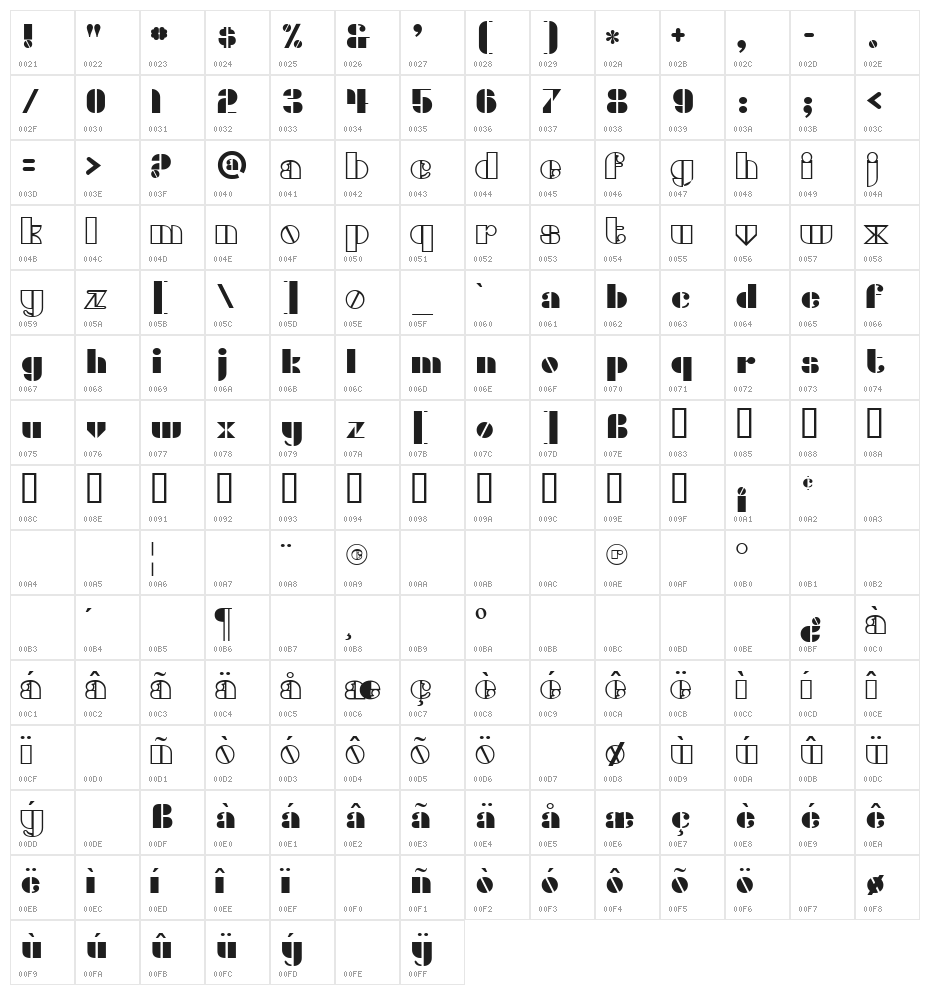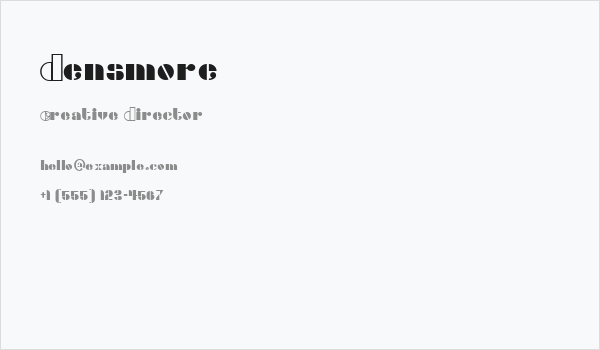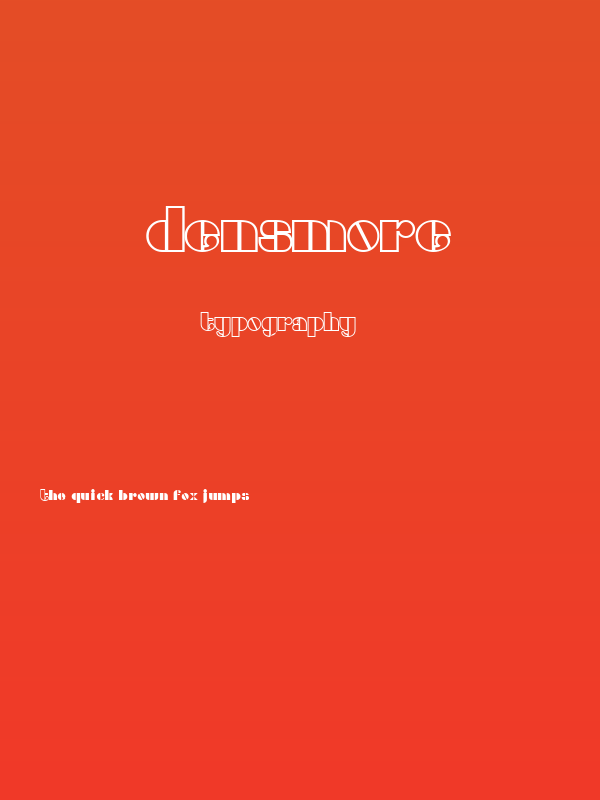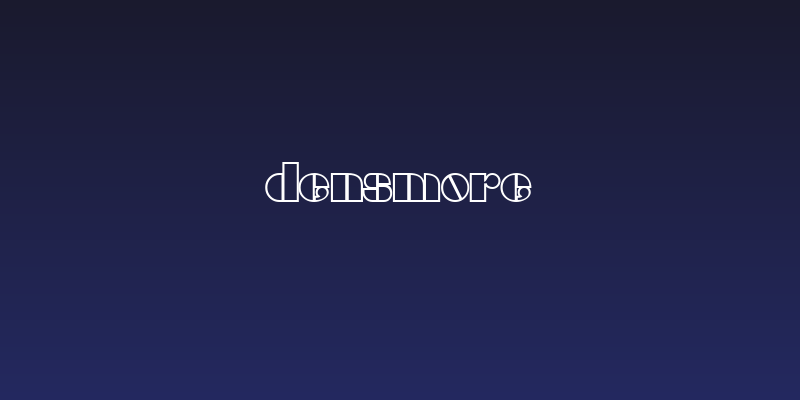
Densmore Font
| Область применения | Logos, Headlines, Posters |
| Рекомендуемые проекты | Ideal for branding, posters, album covers, and any project requiring a bold, modern aesthetic. |